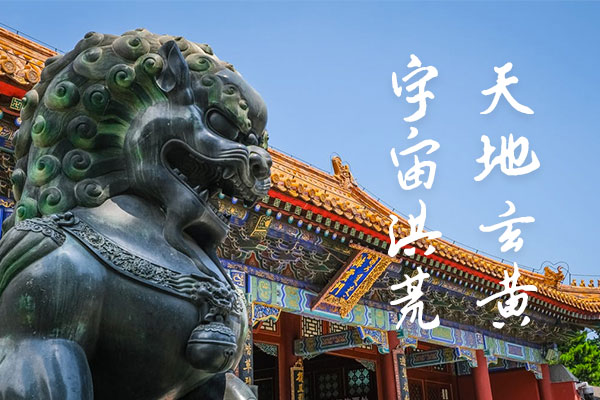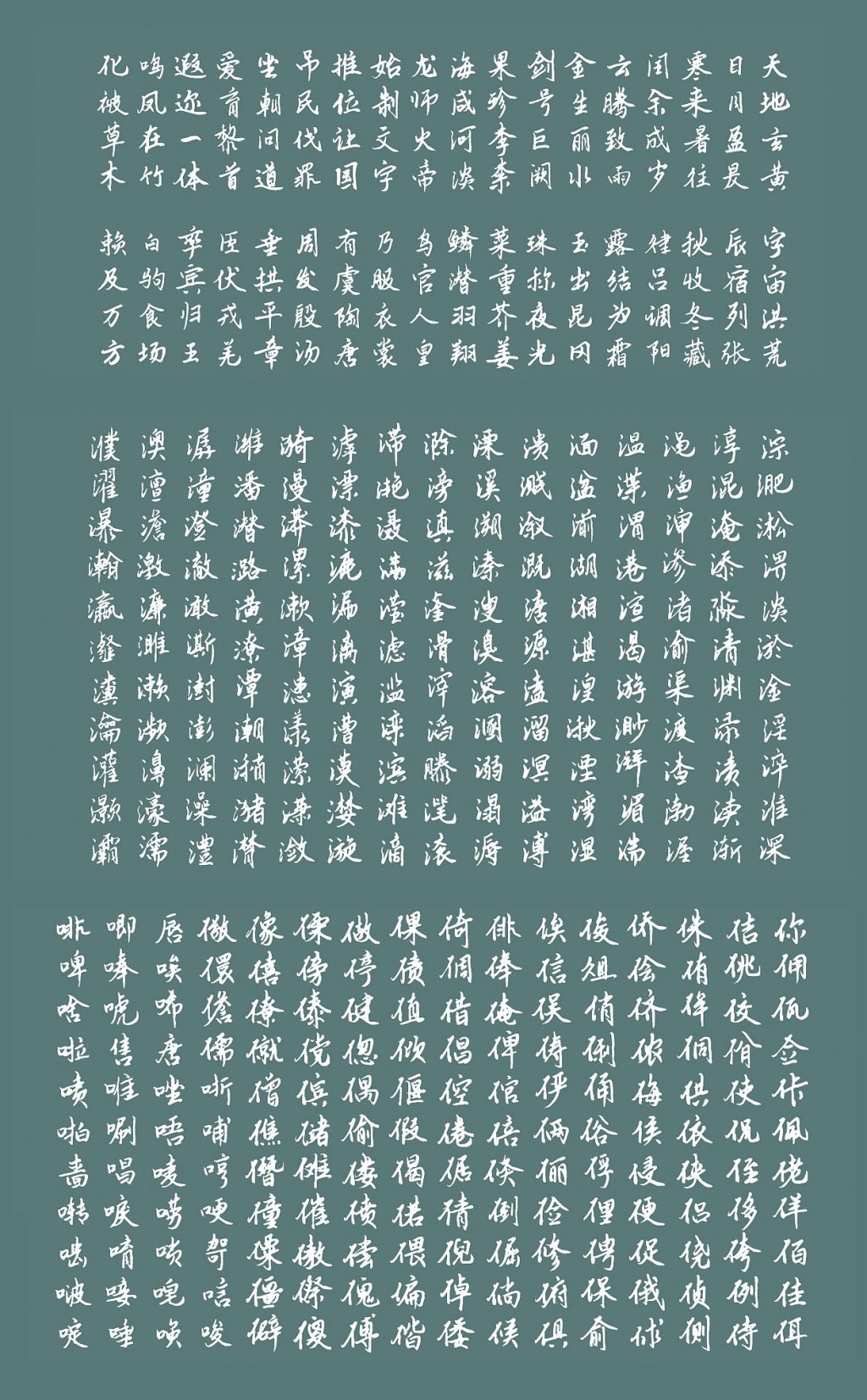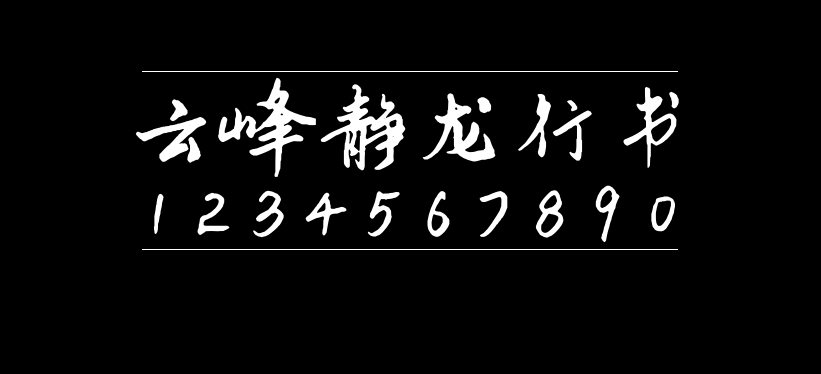
云峰静龙行书
云峰静龙行书是云峰字库推出的首款免费商用字库,行书字体特点是端正平稳,放纵流动。
云峰静龙行书字体将比较复杂的笔画变的更加的简单省略,点画之间的呼应是用勾、挑、牵丝来进行加强的,用圆转的笔画代替了方折的笔画。
云峰静龙行书已包含GB2312标准的6763字,简体支持得很好,可以放心使用。